本文要介紹一款很實用的網路服務「Better Font Finder」,顧名思義就是更容易發掘好字型的線上工具,Better Font Finder 會以更直觀、可視化方式來顯示 Google Fonts,將各種字型並列在一起,方便找出其中細節差異,而不是像一般字型網站使用專業術語分類。使用者只需要透過網站左側的「篩選器」來調整字型列表,點選字型可連結到 Google Fonts 來找到更多資訊。
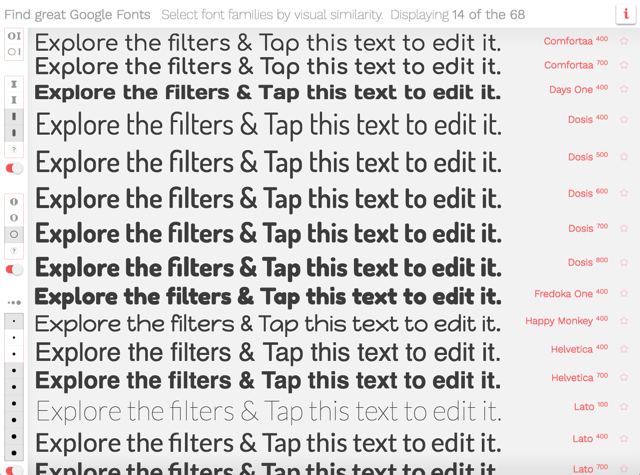
舉例來說,很多人可能都聽過襯線(Serif)和無襯線(Sans-Serif)兩種字體風格,實際上要挑選字型還是不容易從中找出符合你需求的,因為許多字型設計混雜了兩者的視覺特性,如果是直接看字型顯示效果可能會好一些。
開啟 Better Font Finder 網站後,已經有一些預設字型顯示在首頁,主要預覽文字可以從中間看到,右側字型名稱點擊後可以開啟 Google Fonts 頁面。如果想要標記字型可勾選最右邊星號圖示,讓你在比較不同字型時更輕鬆一些。
最主要功能「篩選器」在網站左側,從最上排挑選襯線字(Serif)或是無襯線字(Sans-Serif),網站中間會有一個大大的提示畫面,相當有趣,從畫面中的 O、I 顯示樣式就能知道這兩種字型風格的主要差異。
下方可以選擇你要的字體「I」樣式(其實就是字型的風格),例如有些是圓角、有些則是直角,有些會在邊邊加上襯線修飾效果。可以選擇多種樣式來一次顯示於首頁,方便比較各種字型的顯示感覺。
此外,也能從字元「O」的風格下去挑選。Better Font Finder 非常視覺化,選擇後中間會出現你剛才選擇的風格。
最後,點擊預覽字後可從上方挑選要預覽的不同字串,例如大寫英文字母、數字及標點符號甚至是最常見的 The quick brown fox jumps over the lazy dog ,當然你也可以直接輸入任何預覽文字來查看效果。